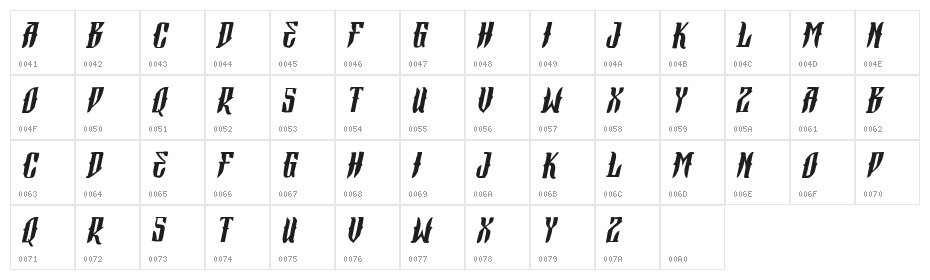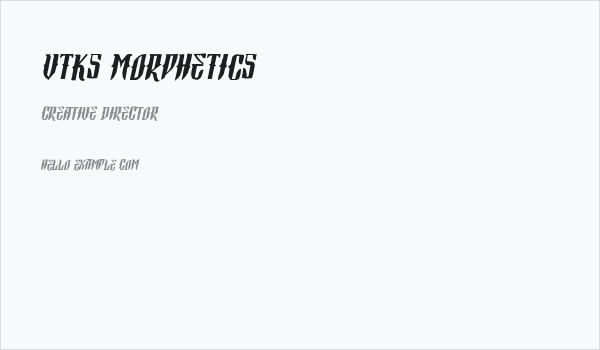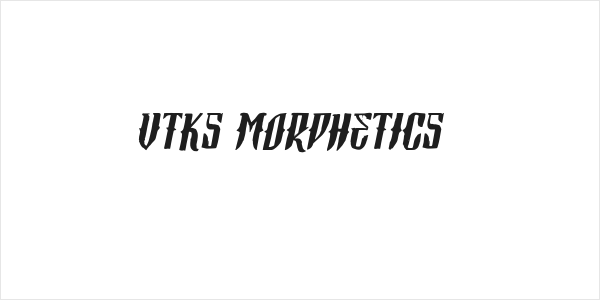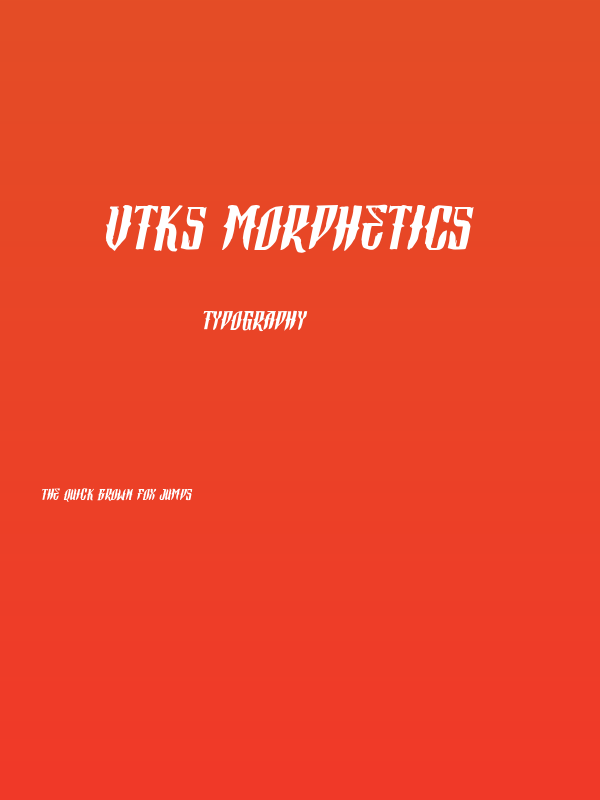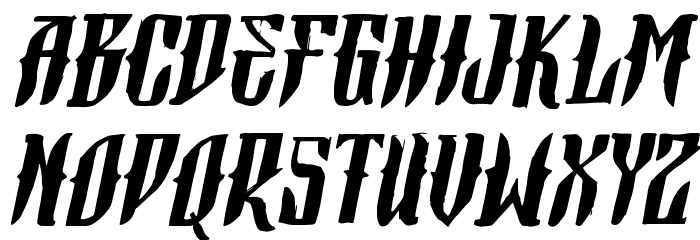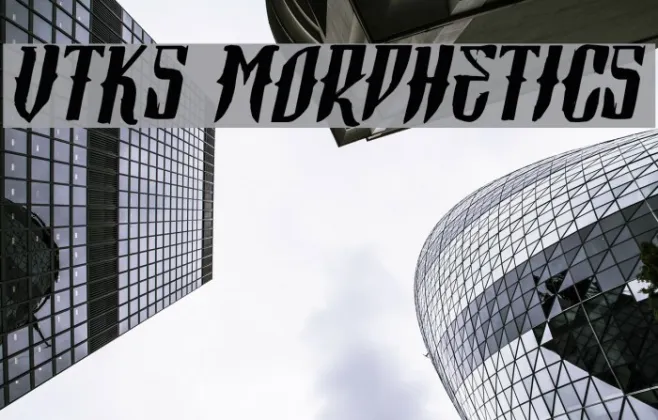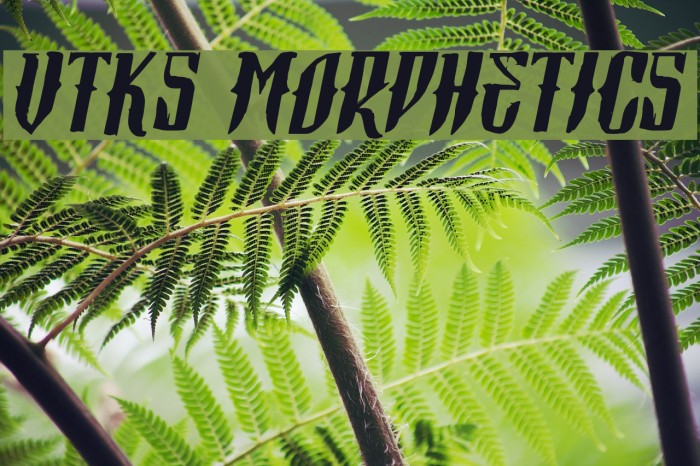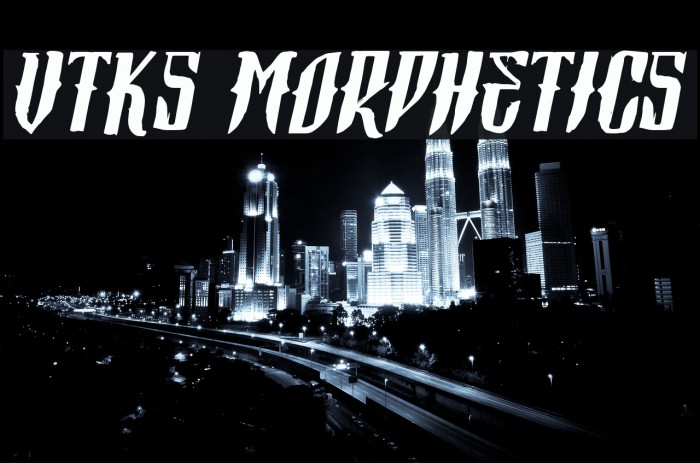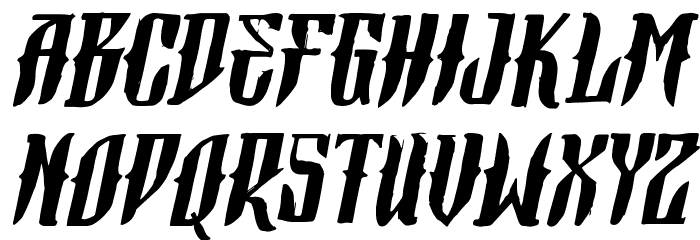
Vtks Morphetics 2 Font
✎ Gothic
| Gesamtstil | Gothic, Decorative |
| Vorgeschlagene Projekte | Ideal for album covers, posters, logos, and any design needing a bold, gothic touch. |